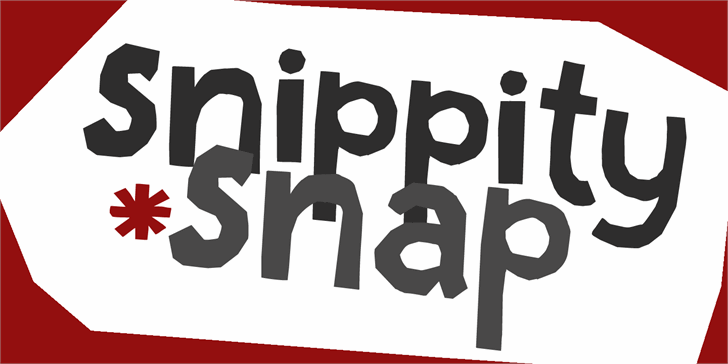
Aqui está uma breve descrição em português para a página de download da font ‘DK Snippity Snap’: A DK Snippity Snap é uma fonte display minimalista e moderna, ideal para criar um visual chamativo em projetos digitais. Desenvolvida pelo designer Hamilton, esta fonte combina elementos simples com uma pitada de simplicidade que se torna muito versátil no mundo das criações digitais. Suas linhas retas e sua disposição minimalista fazem dela uma opção perfeita para criar headlines chamativas ou textos de destaque em websites, banners e publicações online. A fonte é pura e direta, oferecendo um estilo único que combina bem com projetos modernos. É importante destacar que a DK Snippity Snap está disponível apenas sob uso pessoal gratuito. Para qualquer aplicação comercial ou no desenvolvimento de jogos, aplicativos ou softwares, você precisará adquirir uma licença do designer Hamilton diretamente em seu site: hanodedfonts.com.